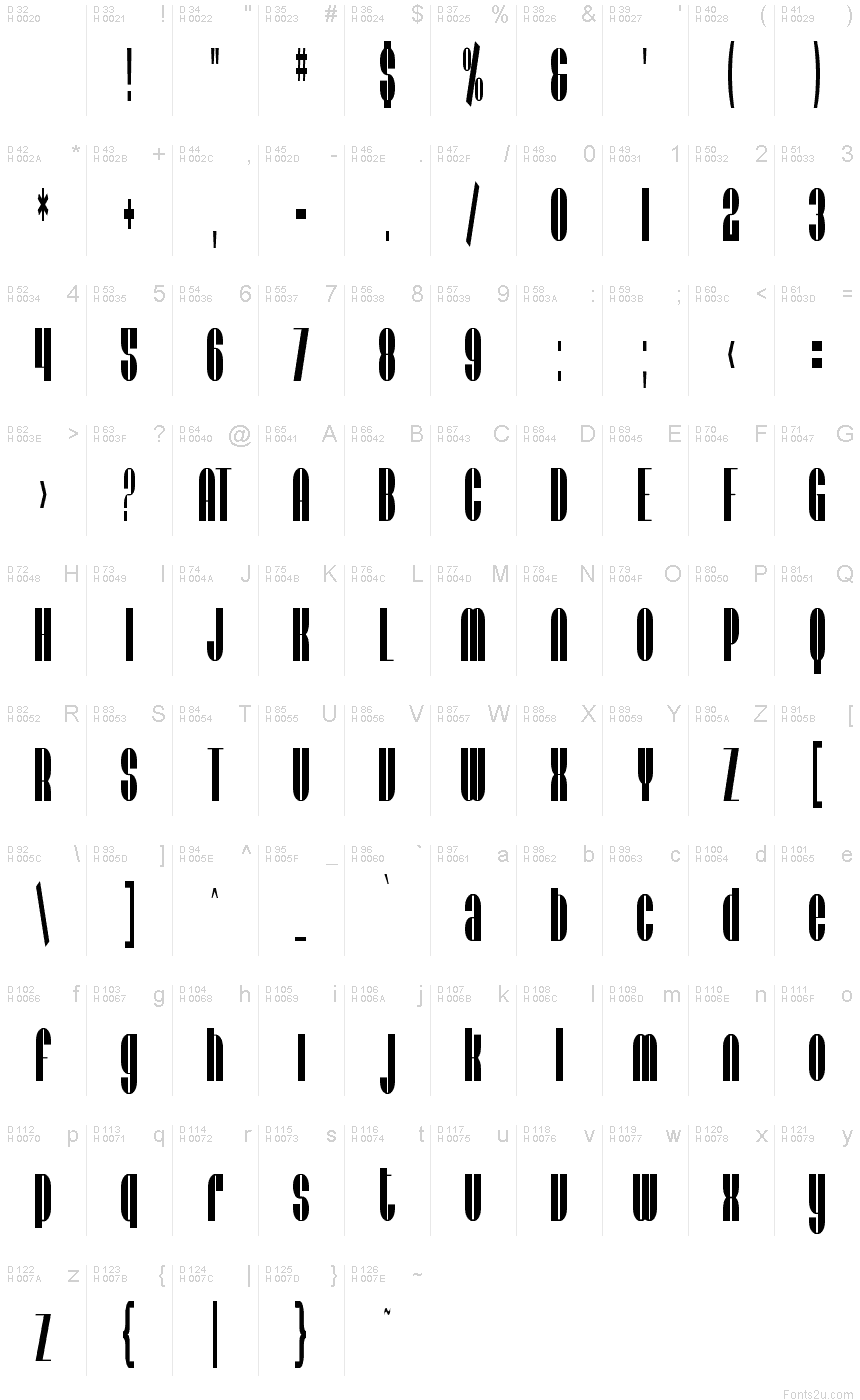
SF Baroquesque od ShyFoundry to bezpłatny retro font typu display z wyraźnym klimatem Art Déco. Litery są wysokie, wąskie i pełne dramatyzmu, a solidne czarne kształty rozdzielone są cienkimi, pionowymi nacięciami, co nadaje alfabetowi plakatowy rytm i teatralny sznyt późnych lat 20. XX wieku.
Świetnie sprawdzi się w menu koktajlowych, brandingu modowym, na okładkach albumów, opakowaniach butikowych oraz w napisach tytułowych, gdzie wystarczy kilka słów, by nadać całości charakteru. Jako darmowy krój, SF Baroquesque najlepiej prezentuje się w krótkich nagłówkach, monogramach i na okładkach, ponieważ te wydłużone kształty i jasne, wewnętrzne prześwity najlepiej pracują, gdy mają odpowiednio dużo przestrzeni.
SF Baroquesque
ShyFoundry
Derek Vogelpohl